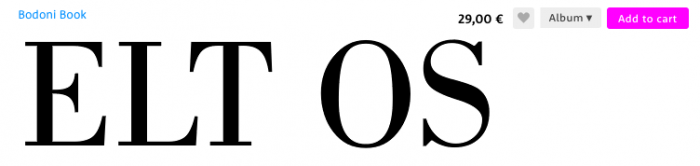
Typografie-Anatomie: Pendant zu Haarlinie
wie nennt man bei einer kontrastreichen Schrift die Buchstabenelemente, die fetter gezeichnet sind als die Haarlinien?
„Stamm“ macht bei rechtwinklig konstruierten Buchstaben Sinn (E,F,H,…), aber bei Buchstaben mit Rundungen (C,G,O, …) scheint mir „Stamm“ nicht das richtige Wort zu sein.
Wie könnte man das bezeichnen?
Wurde das hier nicht kürzlich mal in einer Diskussion als »Schattenlinie« bezeichnet? Es kann aber sein, dass ich mich irre …  :-?
Ich hoffe es gibt einen häufiger verwendeten Ausdruck, der in meinem Hirn bereits schlummert, sonst muss ich den Begriff zusätzlich beschreiben. :nana:
Die ersten drei Buchstaben sind klar. Die Verdickungen kann man ohne Probleme als „Stamm bezeichnen“. Bei runden Formen macht das mMn aber nicht so viel Sinn, weil der Begriff „Stamm“ eine gerade Strecke impliziert. Möchte ich in einem Text auf die „dicke Seite“ des S hinweisen, so fehlt mir das typografische Vokabular um eben diese Seite zu benennen. Stamm klingt falsch.
Ich verstehe Gegenwind so, dass er die dicke Linie im Gegensatz zur Haarlinie innerhalb eines Buchstabens mit einem Fachbegriff beschreiben möchte – ganz unabhängig davon, ob es sich um eine Gerade oder um eine Kurve handelt.
Die Anatomie der Buchstaben sagt "Bogen" dazu.
Die Kurve wird dort als der richtungsändernde Teil bezeichnet:
Ich verstehe Gegenwind so, dass er die dicke Linie im Gegensatz zur Haarlinie innerhalb eines Buchstabens mit einem Fachbegriff beschreiben möchte – ganz unabhängig davon, ob es sich um eine Gerade oder um eine Kurve handelt.
So verstehe ich ihn auch. Aber ich würde das Ganze nicht allzu verkomplizieren. Streng genommen kann man bei der abgebildeten Bodoni auch nicht von einer Haarlinie sprechen.